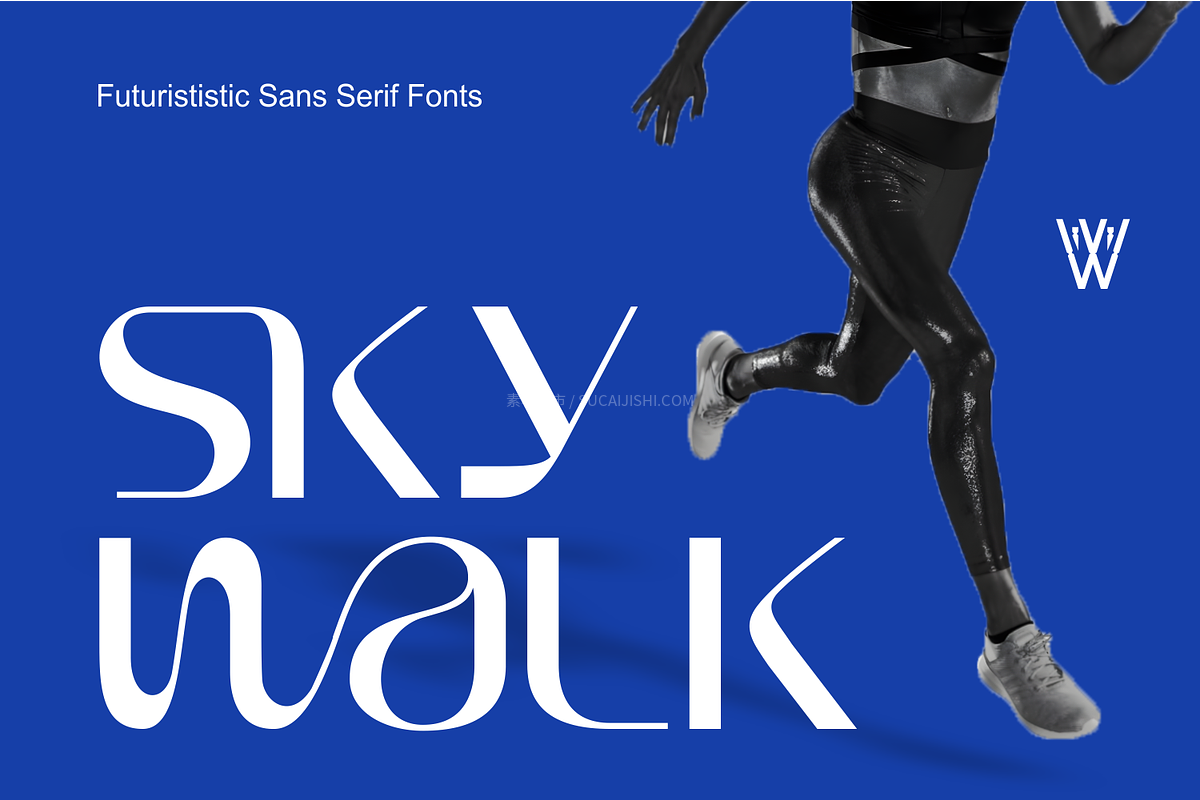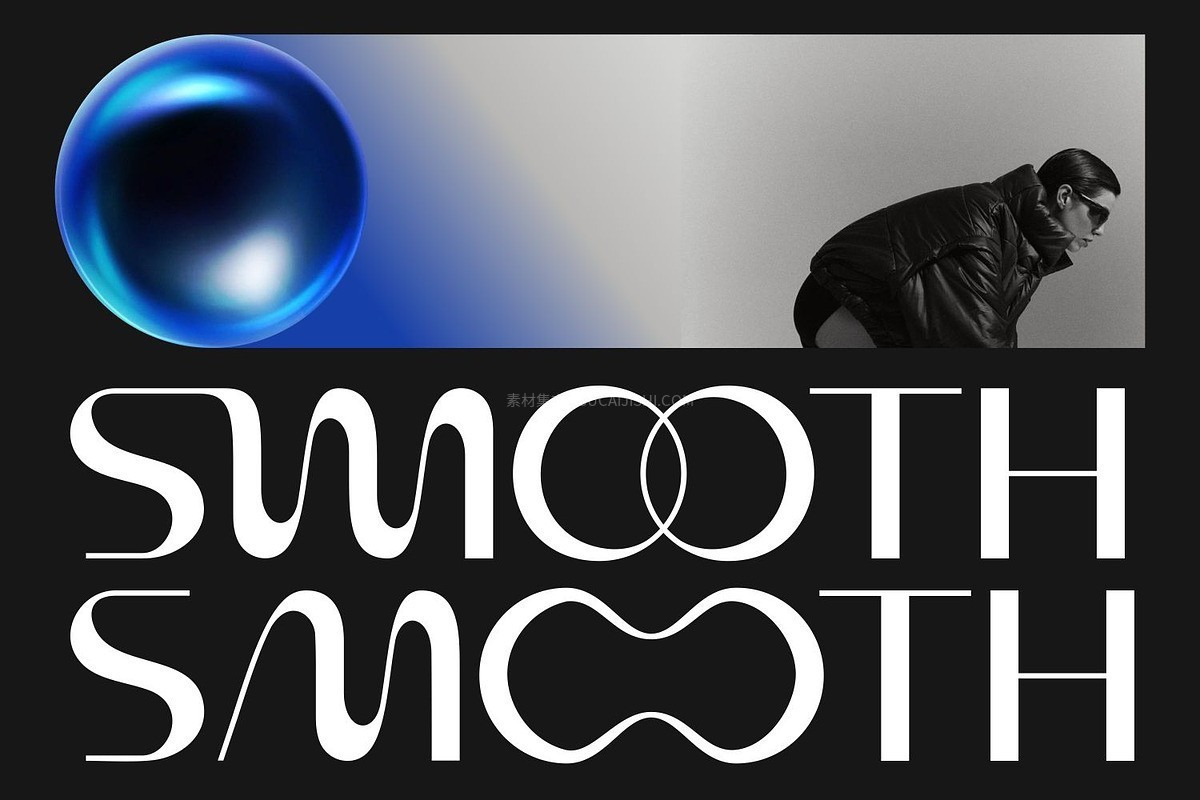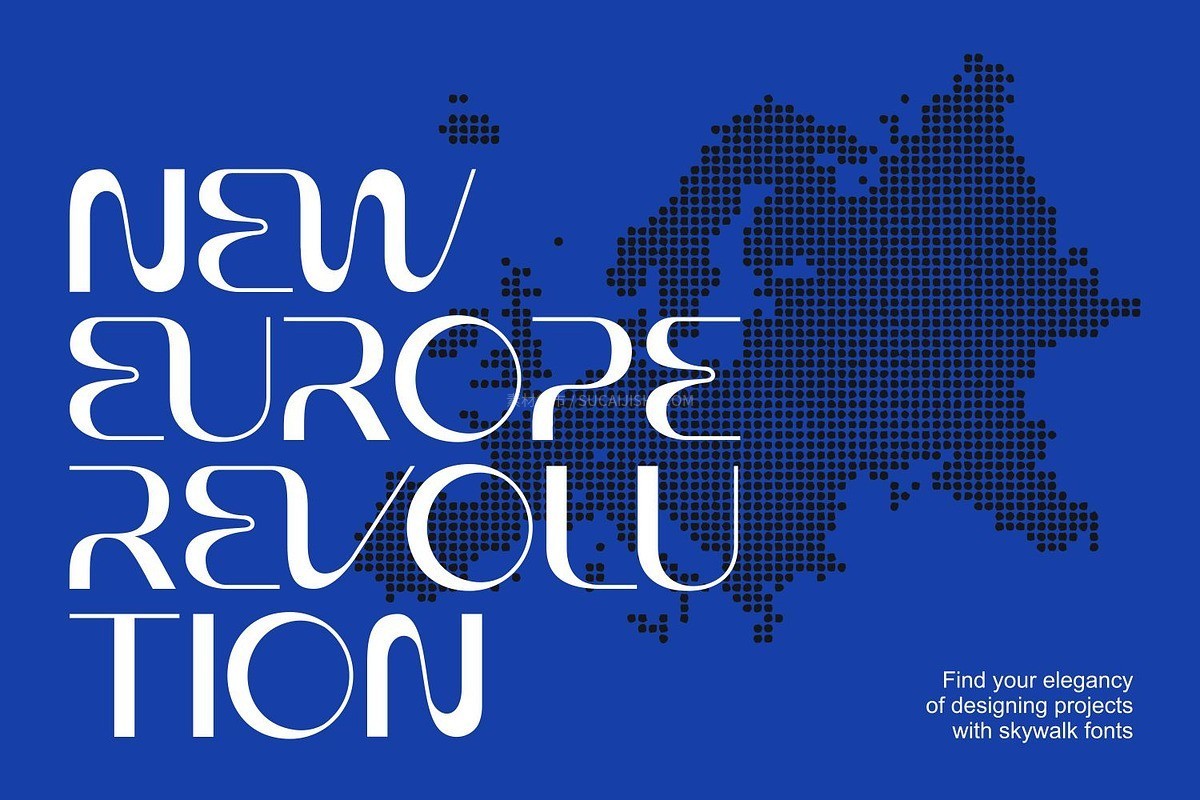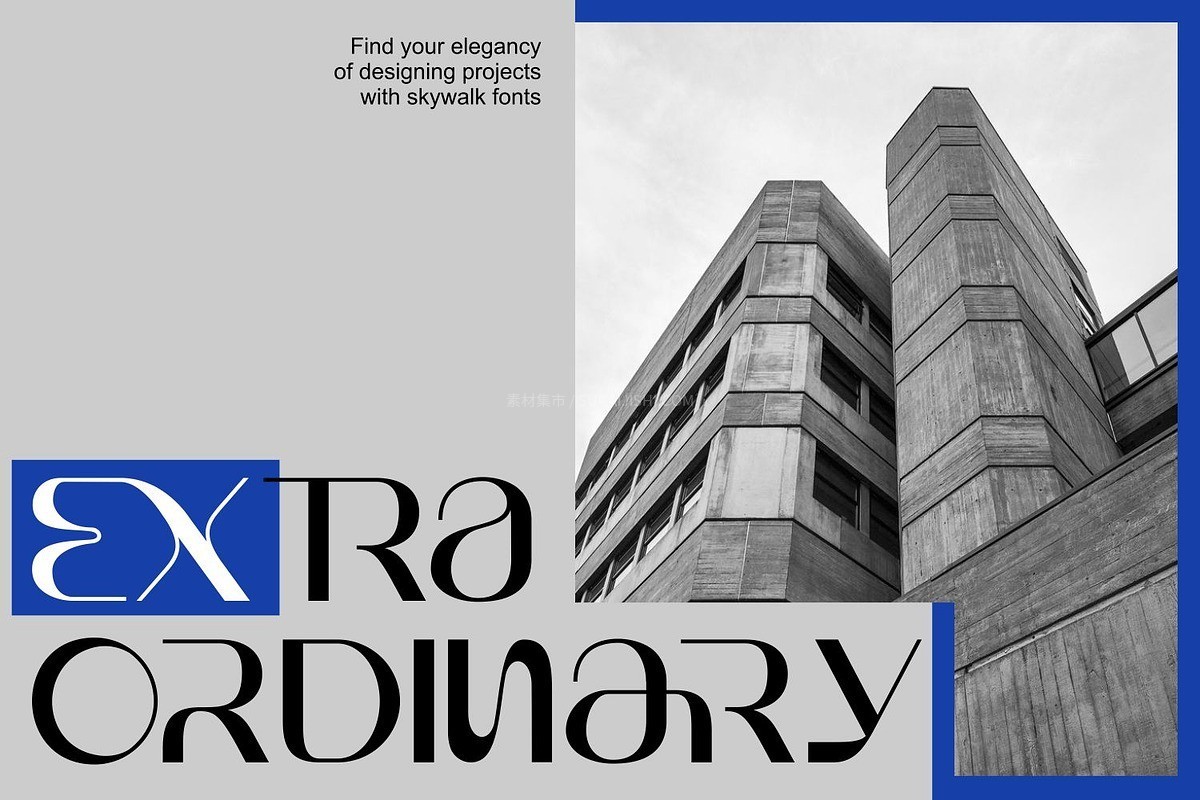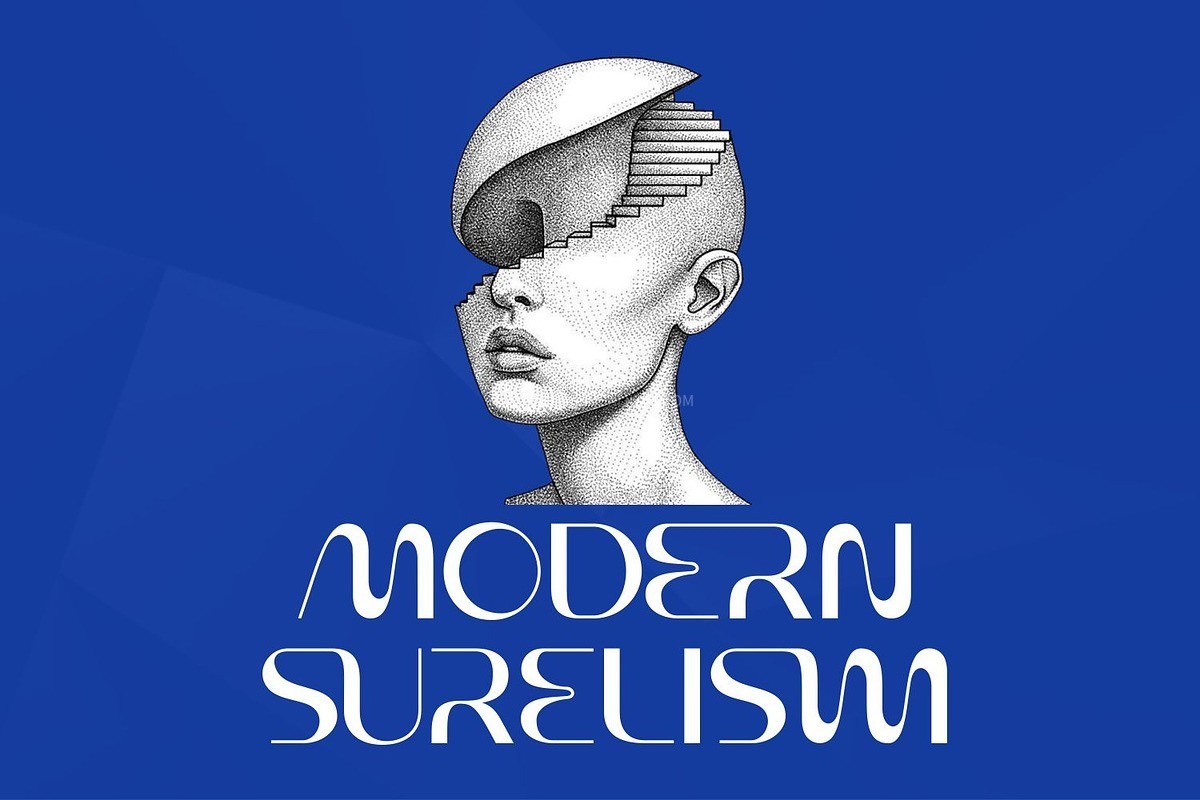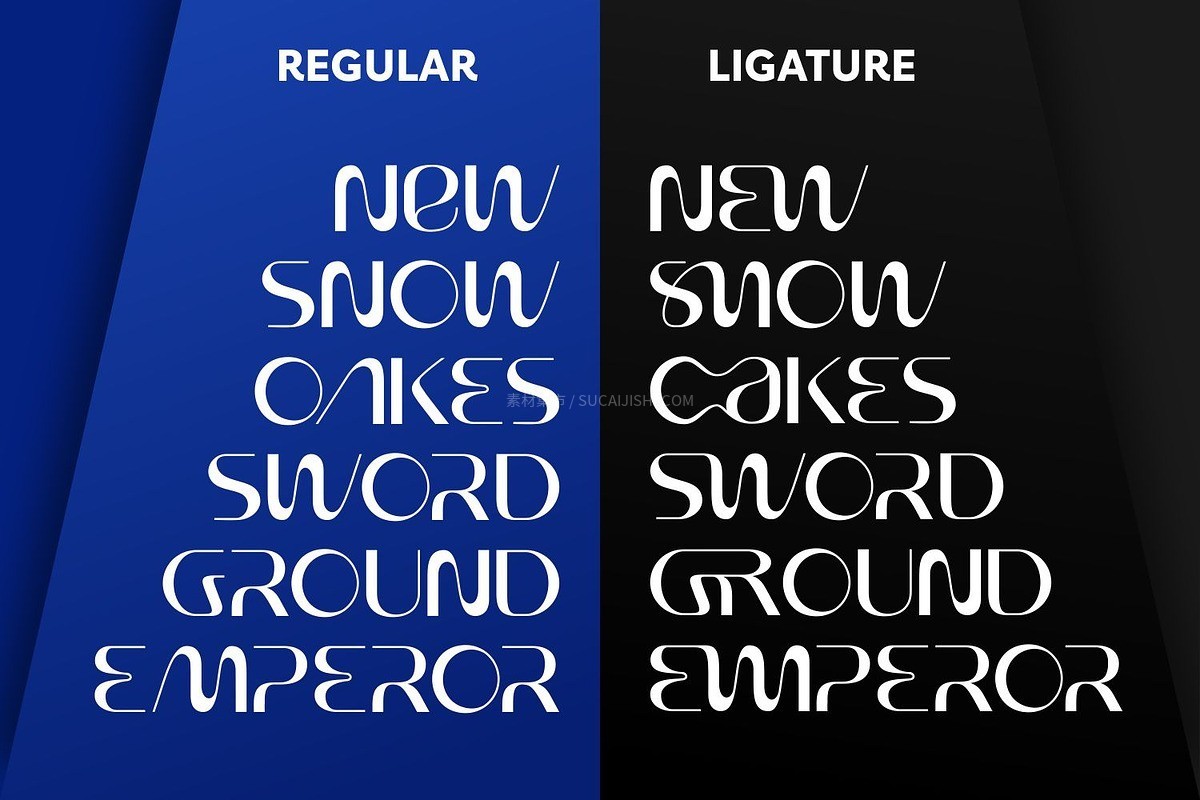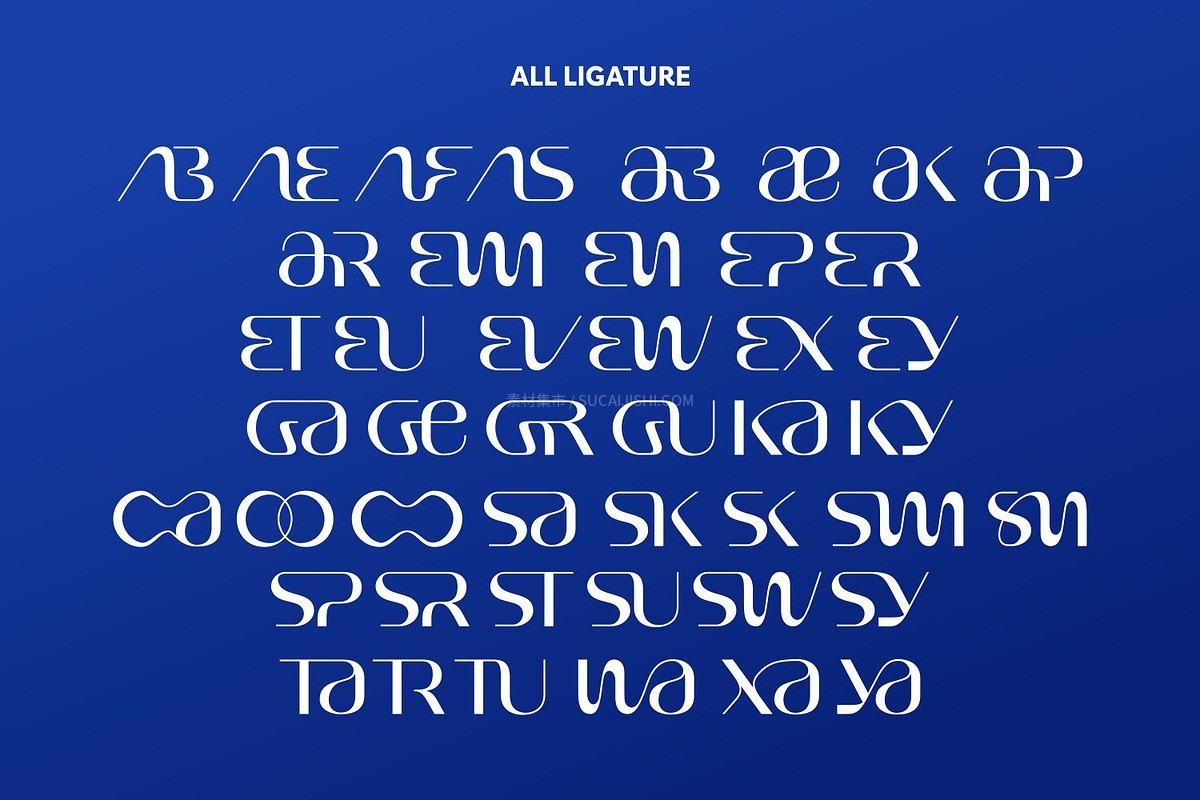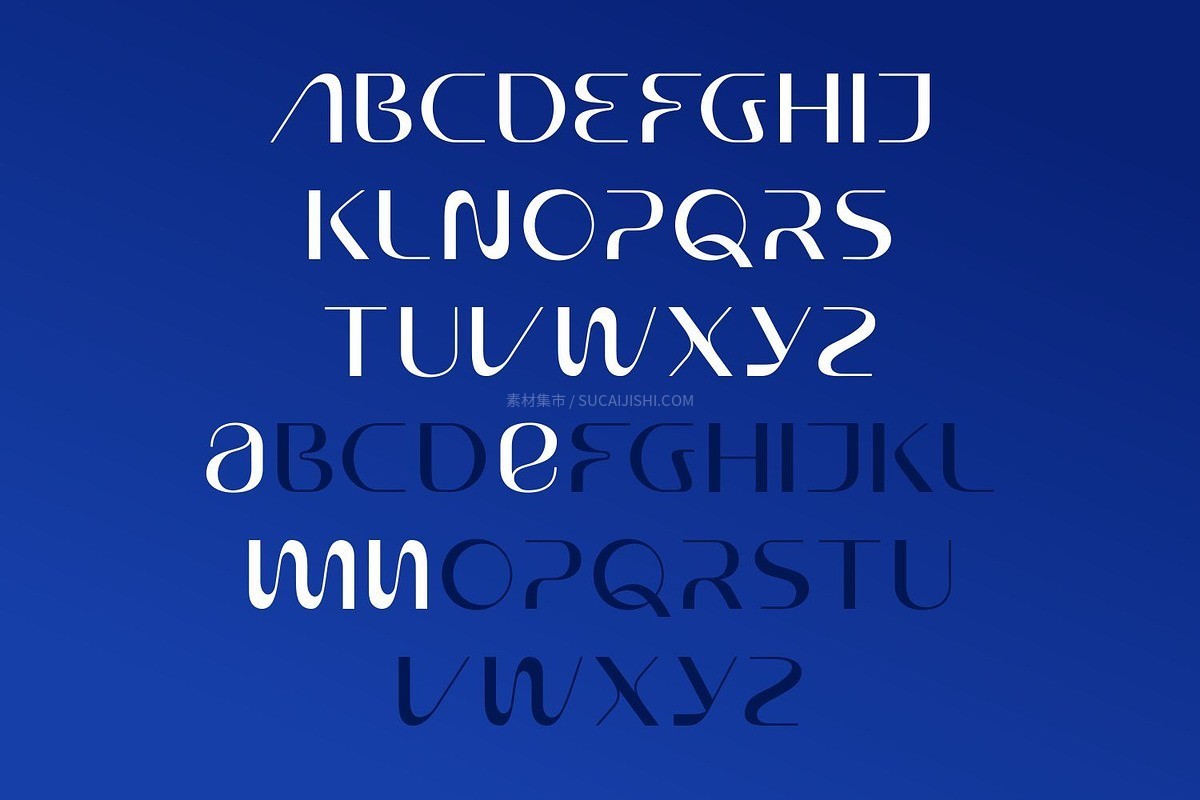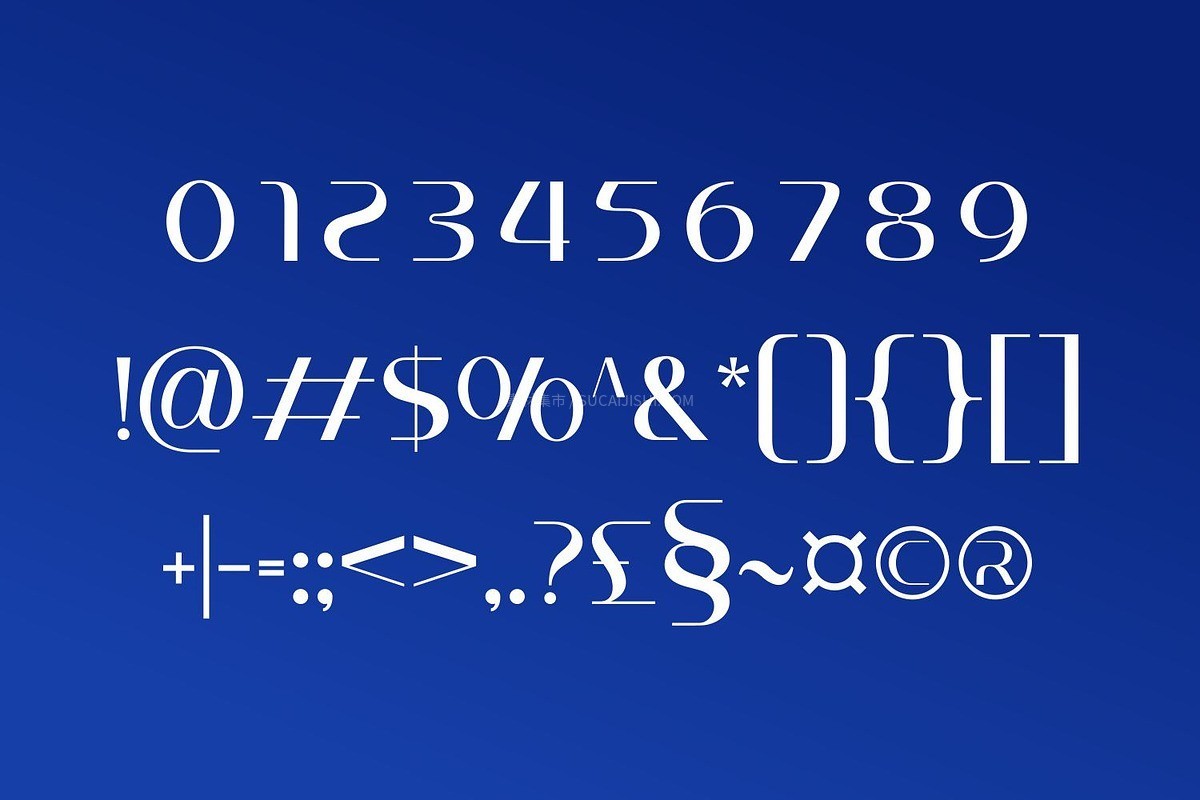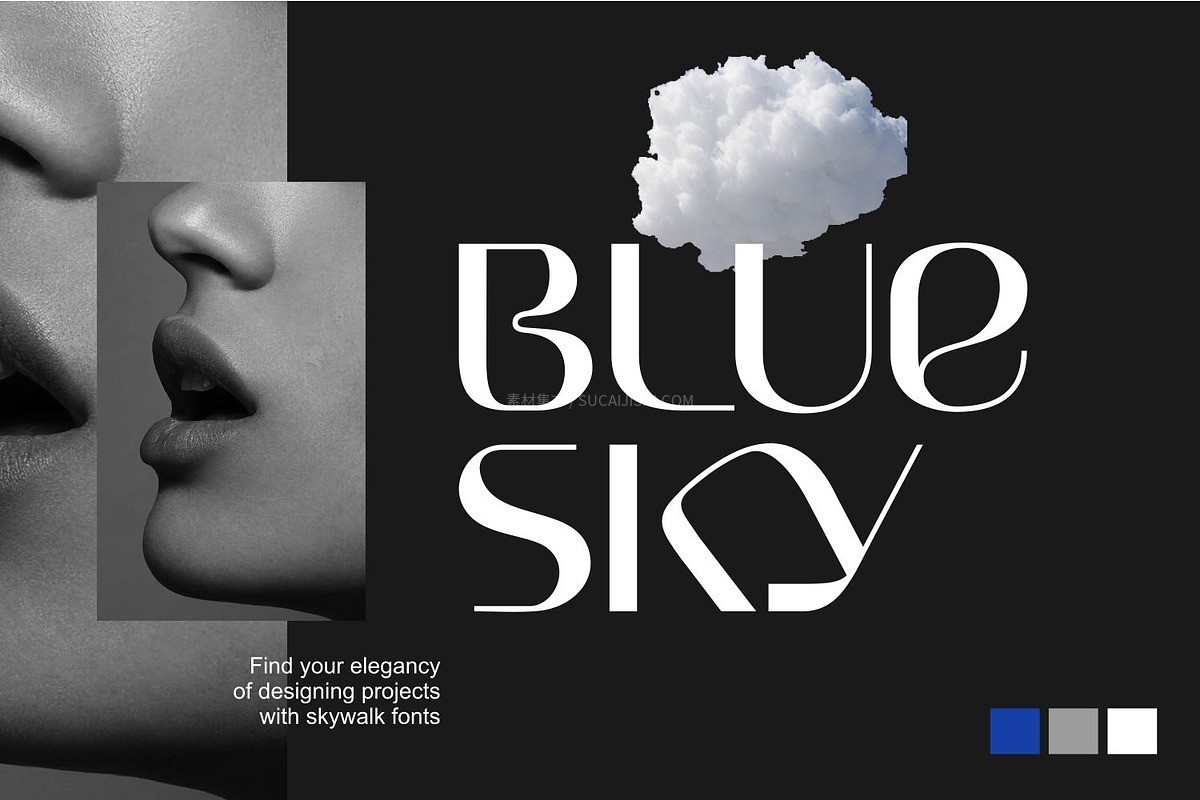
Sky Walk 未来主义优雅衬线英文字体
Sky Walk 是一款极具未来主义风格的优雅衬线英文字体。它深受畅销字体 Moon Walk 的启发,巧妙地将未来科技感与独特的衬线粗细变化相结合,使其在保持前卫的同时更显优雅与百搭。字体包内含纯正的 TTF 和 OTF 格式,能够轻松胜任从大型商业品牌到个人创意的各种规模设计项目。